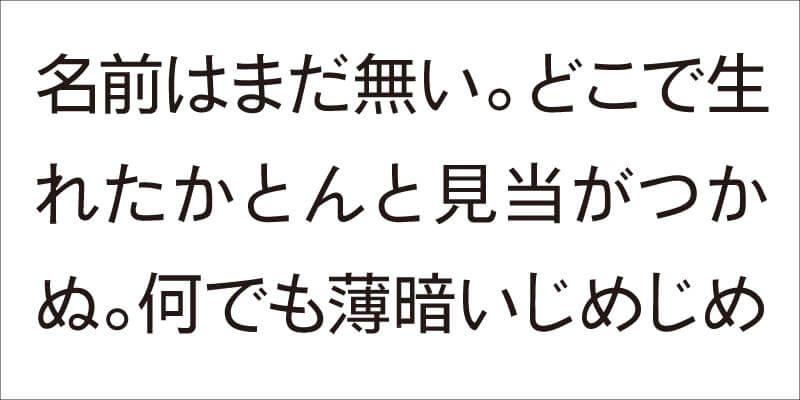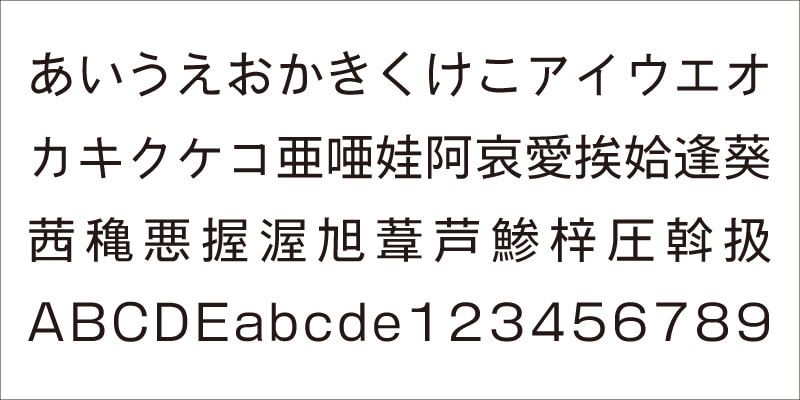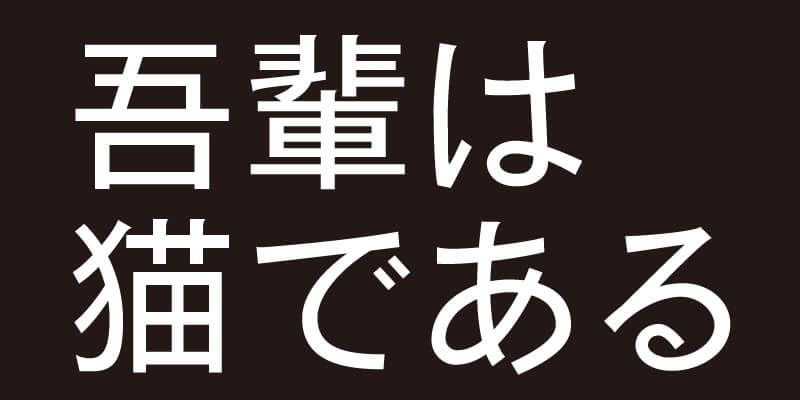
이는 본문용으로 고안된 아름답고 가독성 높은 고딕(산세리프) 서체이며 ‘디지털’ 타이프 디자인의 전형적인 이미지에서 벗어난 것입니다. 일본의 전통적인 산세리프 스타일에 바탕으로 두고 있지만 가나 음소 문자는 친숙한 아우라를 품고 있으며 부드럽고 점잖은 성격을 갖고 있습니다. 이 서체는 작품에 적당한 시각적 긴장을 조성할 뿐만 아니라 노스텔지어의 느낌을 더합니다.